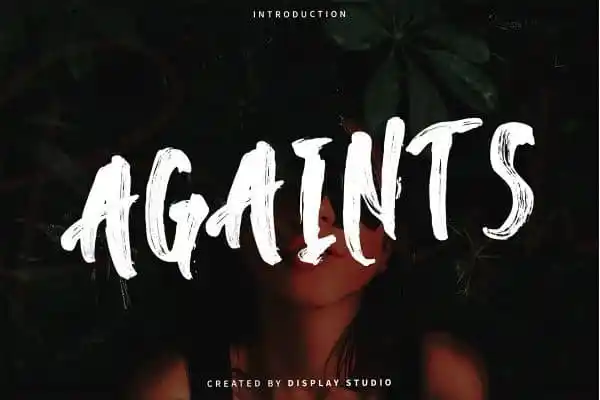
Against Brush Font – Download Grátis
Against Brush Font é uma elegante tipografia script moderna e bold, perfeita para qualquer projeto de design contemporâneo. Desenhada pelo Display Studio, esta fonte oferece versatilidade tanto em linguagem quanto na estética, tornando-a ideal não só para logos de marcas, cartões de convite ou cartas de cumprimento, mas também para um vasto range de trabalhos. Seu design robusto e seus vários elementos de estilo garantem que sua marca fique atraente e profissional em qualquer situação, elevando seu projeto ao próximo nível. Seja você um designer criativo ou um profissional de marketing, Against Brush Font é uma escolha sólida para dar o toque final em seus projetos mais sofisticados.